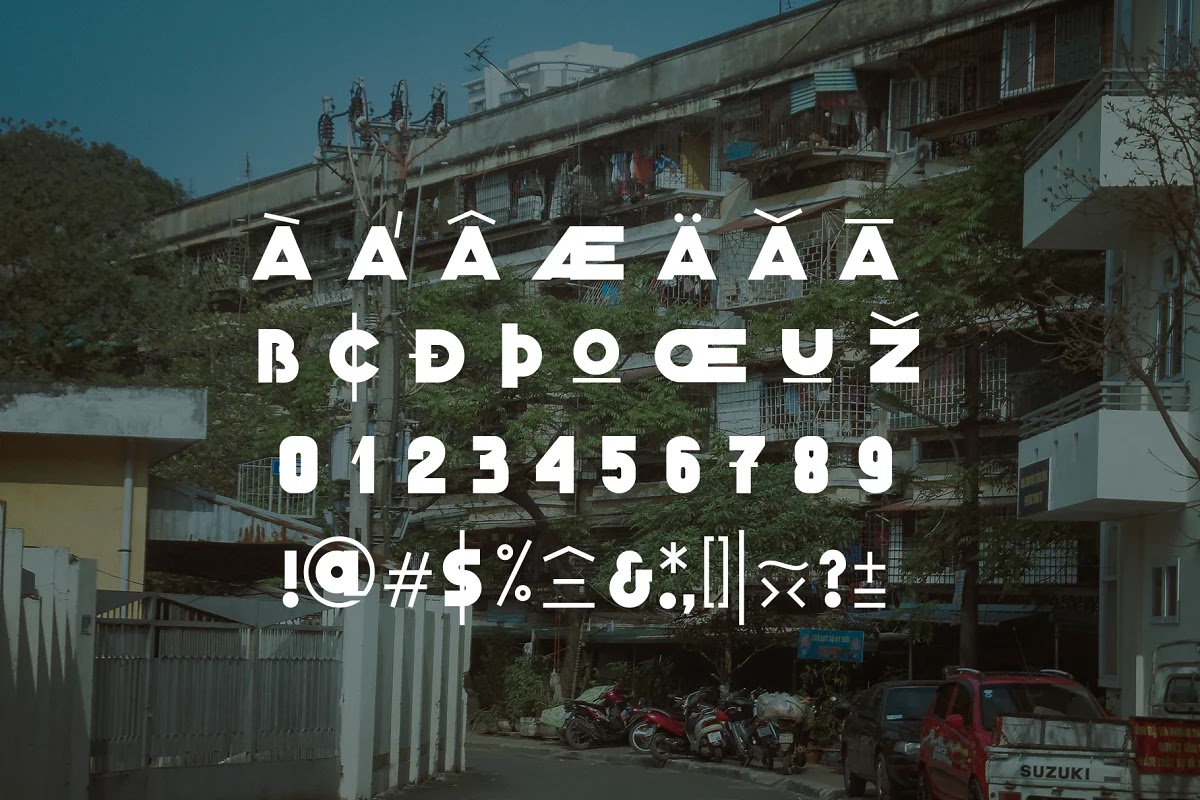
Classique Saigon font Việt hóa là bộ typeface không chân (Sans-serif) mang phong cách Retro độc đáo, được sáng tạo bởi designer Mạnh Nguyễn lấy cảm hứng từ những tấm biển hiệu vẽ tay rực rỡ tại Sài Gòn những năm đầu thế kỷ 20. Với sự kết hợp hoàn hảo giữa hình khối hình học hiện đại và linh hồn hoài cổ của Việt Nam xưa, Classique Saigon typeface đã trở thành lựa chọn hàng đầu cho các dự án thiết kế bao bì, poster và nhận diện thương hiệu truyền thống. Doozypack.vn cung cấp link Classique Saigon font free download chuẩn, giúp bạn sở hữu bộ phông chữ đẳng cấp này mà không lo lỗi dấu tiếng Việt.
Nguồn gốc và đặc điểm nghệ thuật của Classique Saigon Typeface
Để ứng dụng hiệu quả Classique Saigon, designer cần hiểu rõ câu chuyện văn hóa đằng sau từng đường nét của bộ chữ này.
Cảm hứng từ nghệ thuật vẽ bảng hiệu Sài Gòn xưa
Đặc trưng lớn nhất của font Classique Saigon typeface là sự tái hiện lại phong cách vẽ chữ trên các bảng hiệu quảng cáo thập niên 50 – 60 tại miền Nam. Các nét chữ được thiết kế dứt khoát, chắc chắn nhưng vẫn có sự mềm mại nhờ kỹ thuật tinh chỉnh các góc bo. Điều này gợi nhắc đến hình ảnh những tiệm may, tiệm tạp hóa hay những rạp hát kinh điển, tạo nên một không gian hoài niệm vô cùng chân thực và ấn tượng.
Cấu trúc hình học chuẩn xác và hỗ trợ tiếng Việt bản địa
Khác với nhiều bộ font Retro nước ngoài phải qua quá trình Việt hóa thủ công, Classique Saigon được thiết kế bởi người Việt dành cho người Việt. Chính vì vậy, hệ thống dấu thanh (ă, â, đ, ê, ô, ơ, ư) và các dấu sắc, huyền, hỏi, ngã, nặng được đặt ở vị trí cực kỳ cân đối, không đè nét và giữ nguyên được nhịp điệu Typography của chữ gốc. Việc tải font Classique Saigon giúp bản thiết kế của bạn luôn chỉn chu và chuyên nghiệp tuyệt đối.